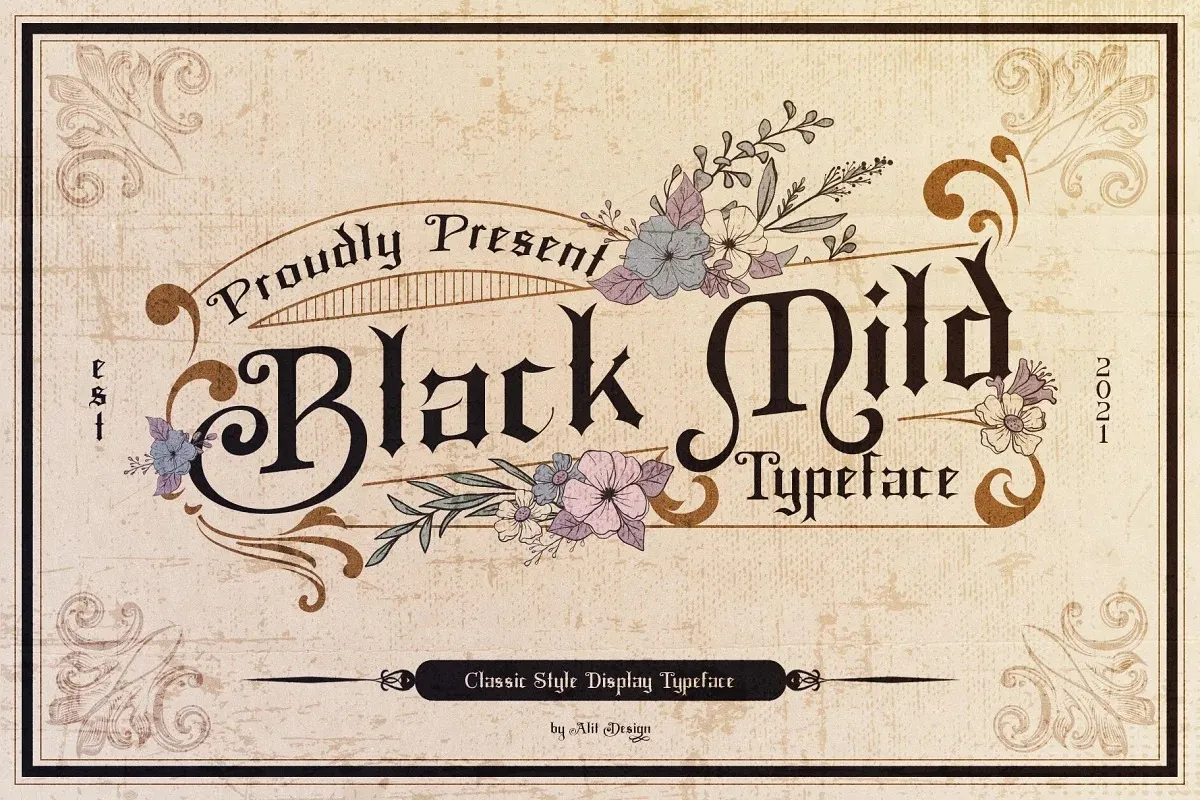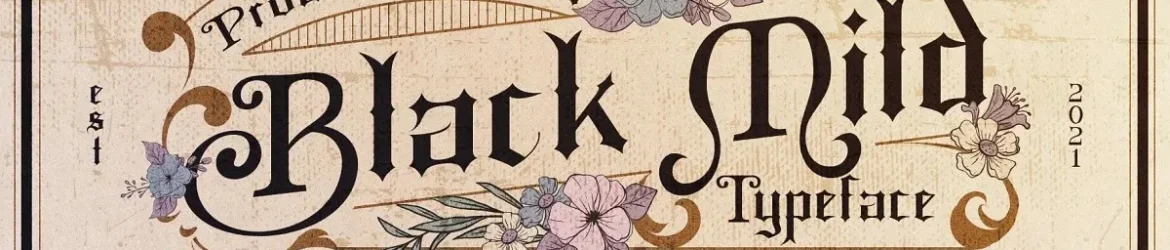
A Black Mild Font é uma opção única para quem busca estilo elegante e moderno combinado com um toque vintage. Criada pelo designer alit design, esta fonte se destaca pela sua forma robusta e marcante, traduzindo o conceito de “Blackletter” em uma linguagem mais contemporânea. Perfeita para trabalhos inspirados no gótico ou na era vitoriosa, a Black Mild é ideal também para criações que combinem rock e vinho. Seja para desenhos de rótulos de bebidas uísque ou projetos mais jovens e descolados, esta fonte mantém o essencial do estilo vintage enquanto inclui um toque moderno, fazendo-a uma opção ideal tanto para designers quanto para quem quer imprimir um design elegante em seus trabalhos. Experimente a Black Mild e explore como ela pode transformar suas criações digitais.